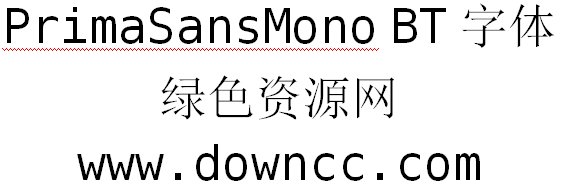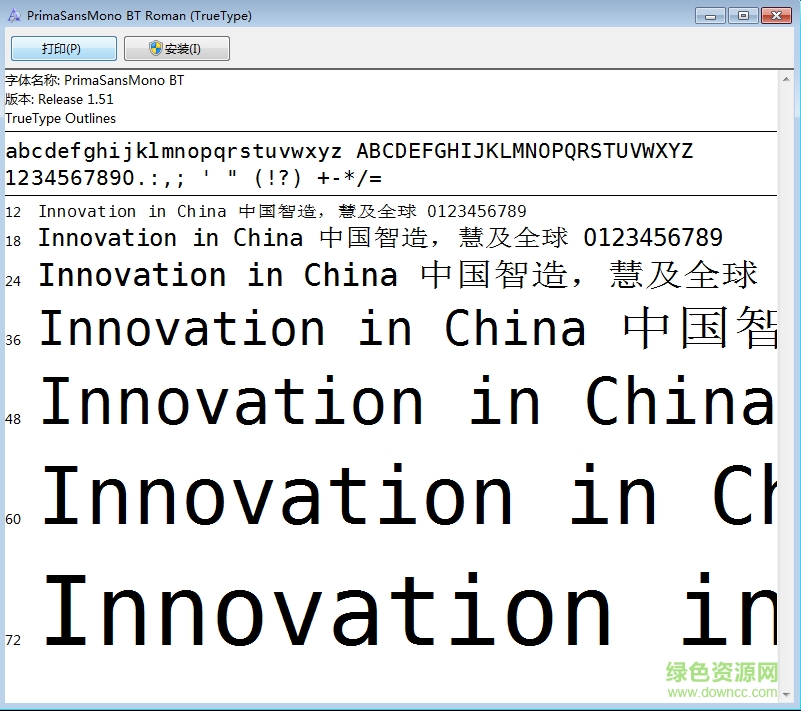
Prima Sans Mono
PrimaSansMono是一款常用的英文字體,也是為編程人員所喜愛的網(wǎng)頁字體,字跡端正清新,使用范圍較廣,喜歡的朋友可以來綠色資源網(wǎng)下載哦!
prima sans mono字體介紹
PrimaSansMono BT Roman字體,共有292個(gè)字符。其風(fēng)格樣式屬于Roman,是PrimaSansMono字體家族的重要字體,可在廣告設(shè)計(jì)、名片設(shè)計(jì)、平面設(shè)計(jì)等行業(yè)使用。